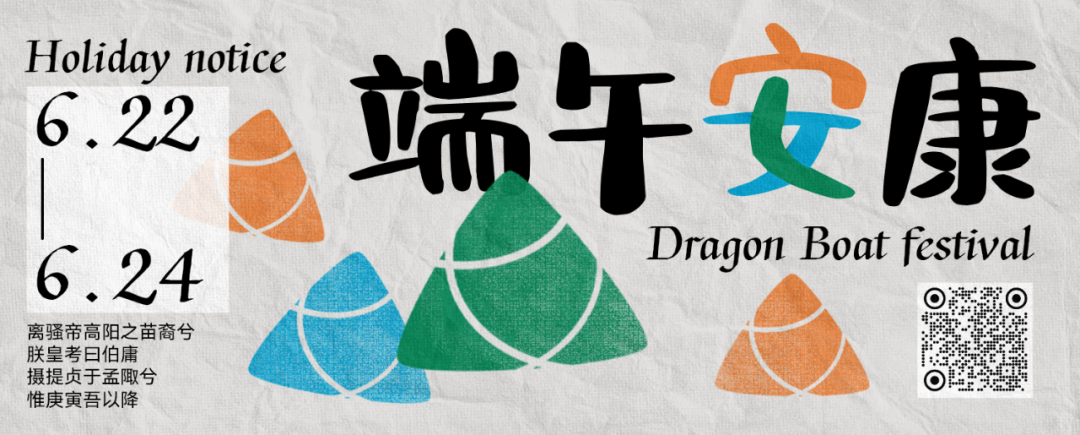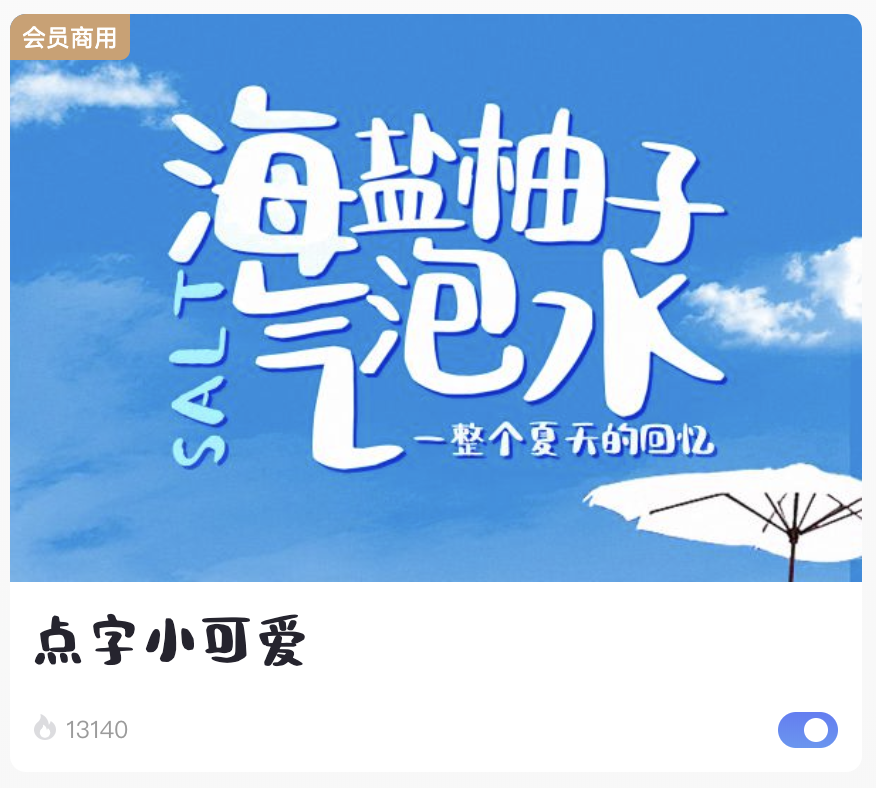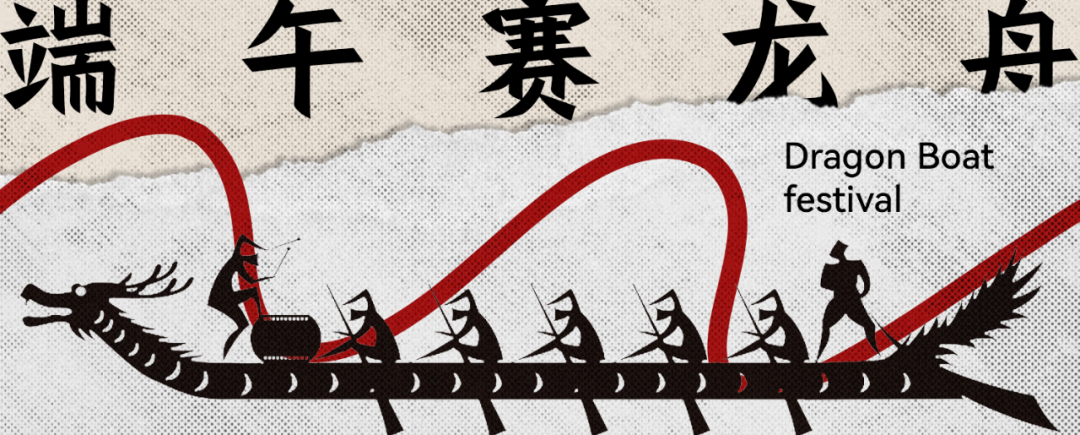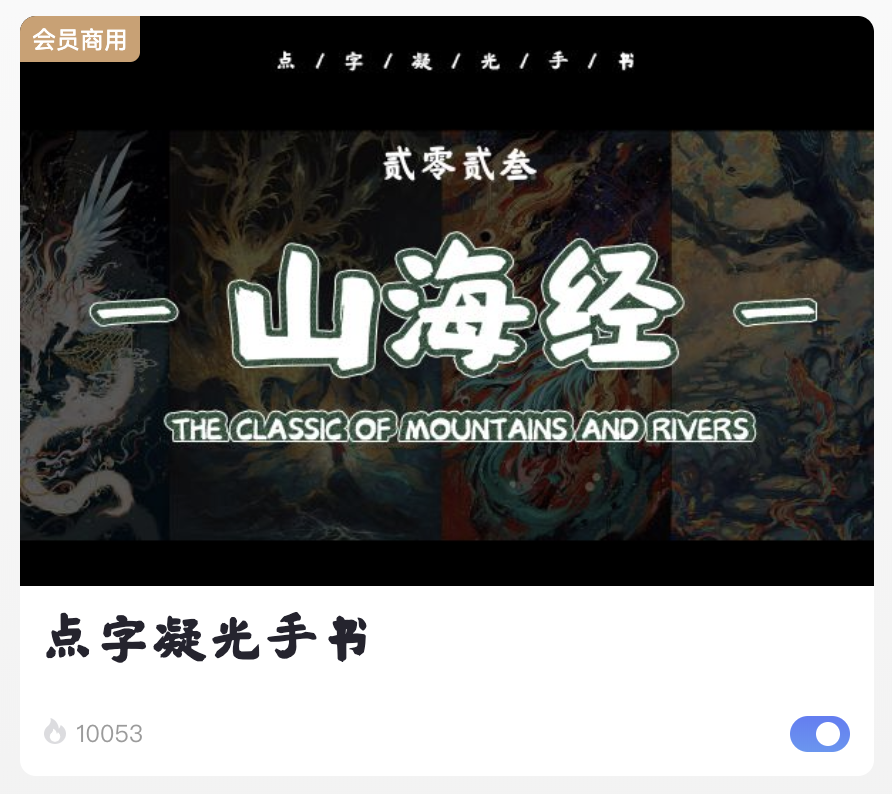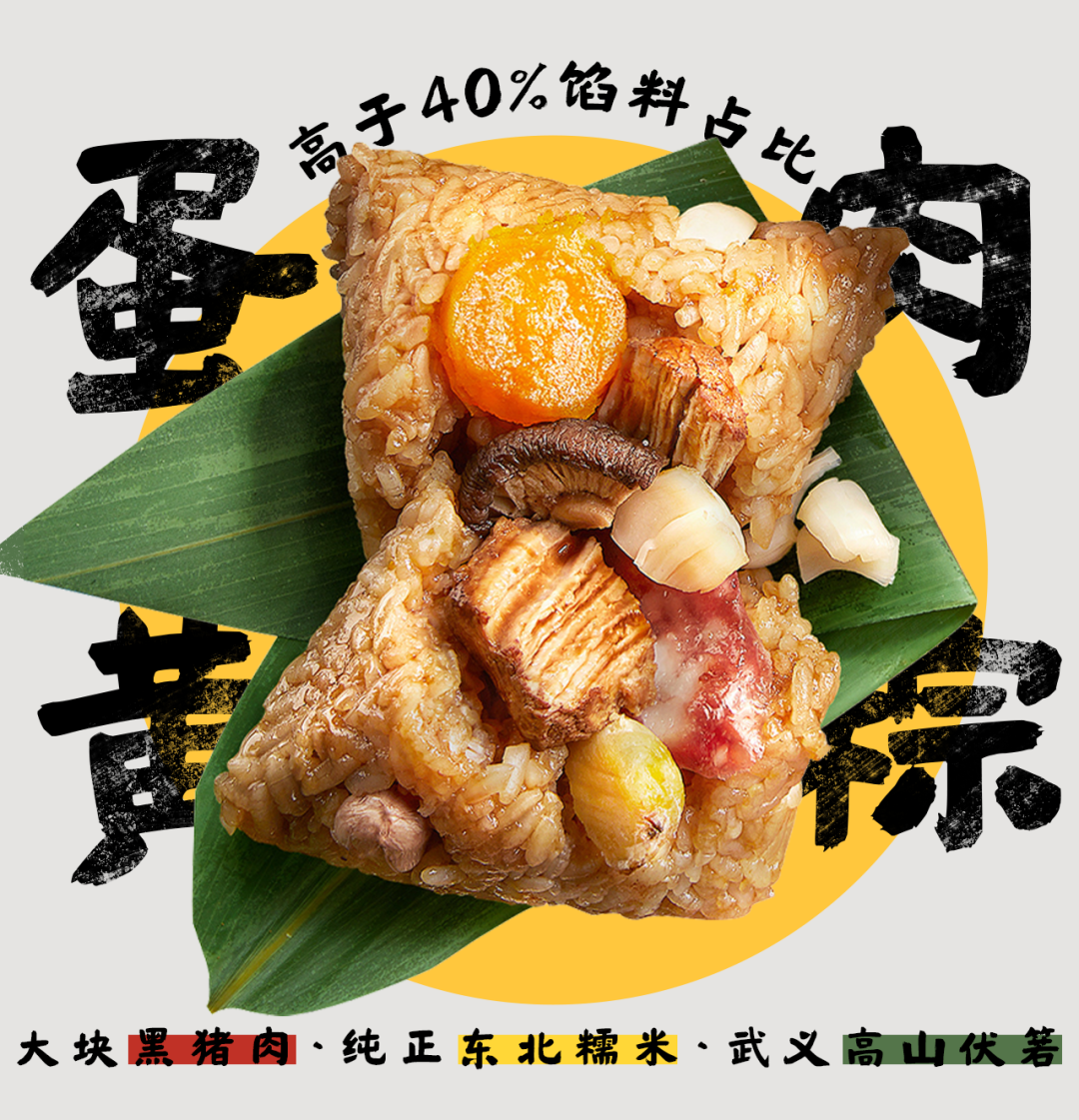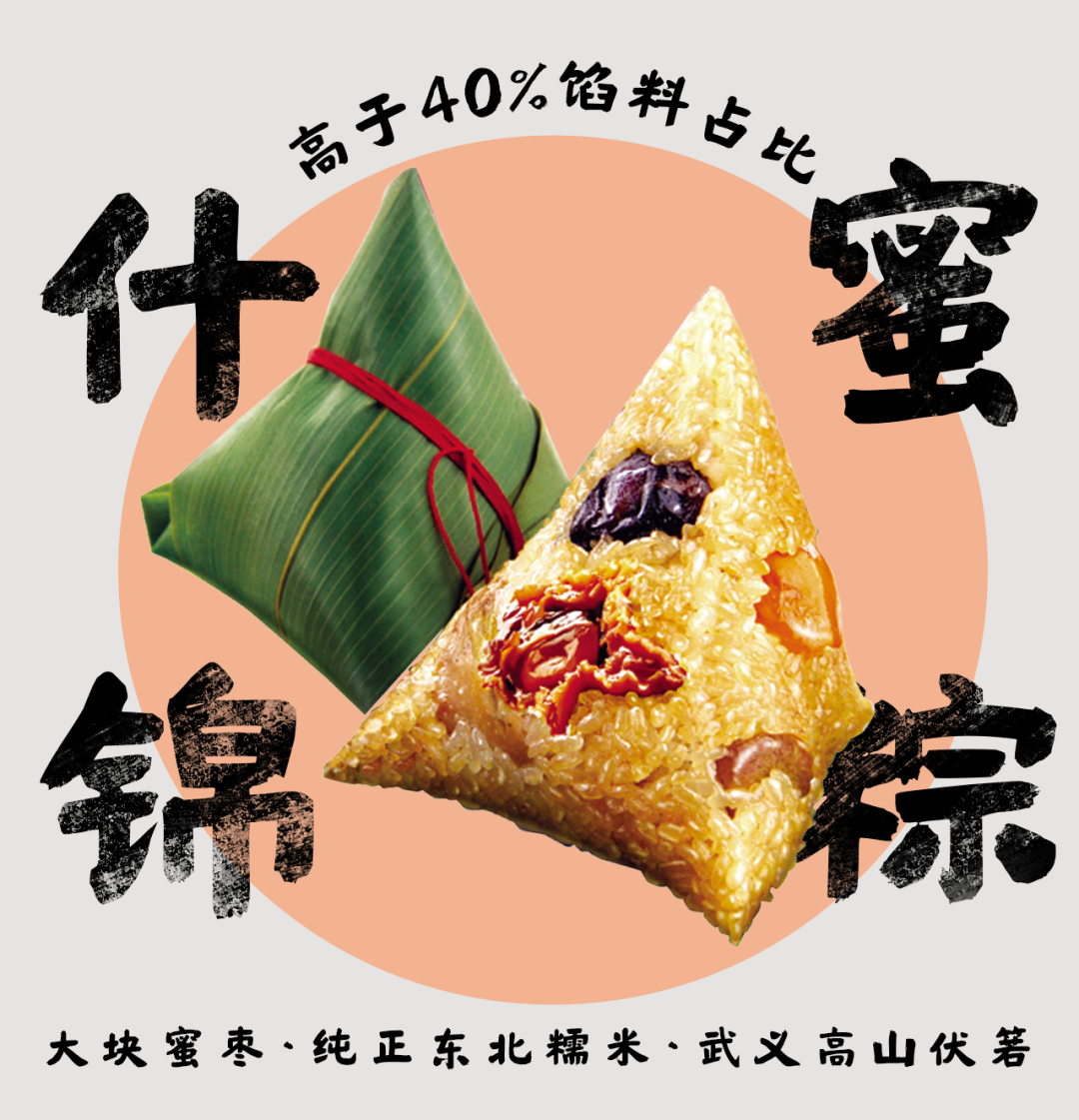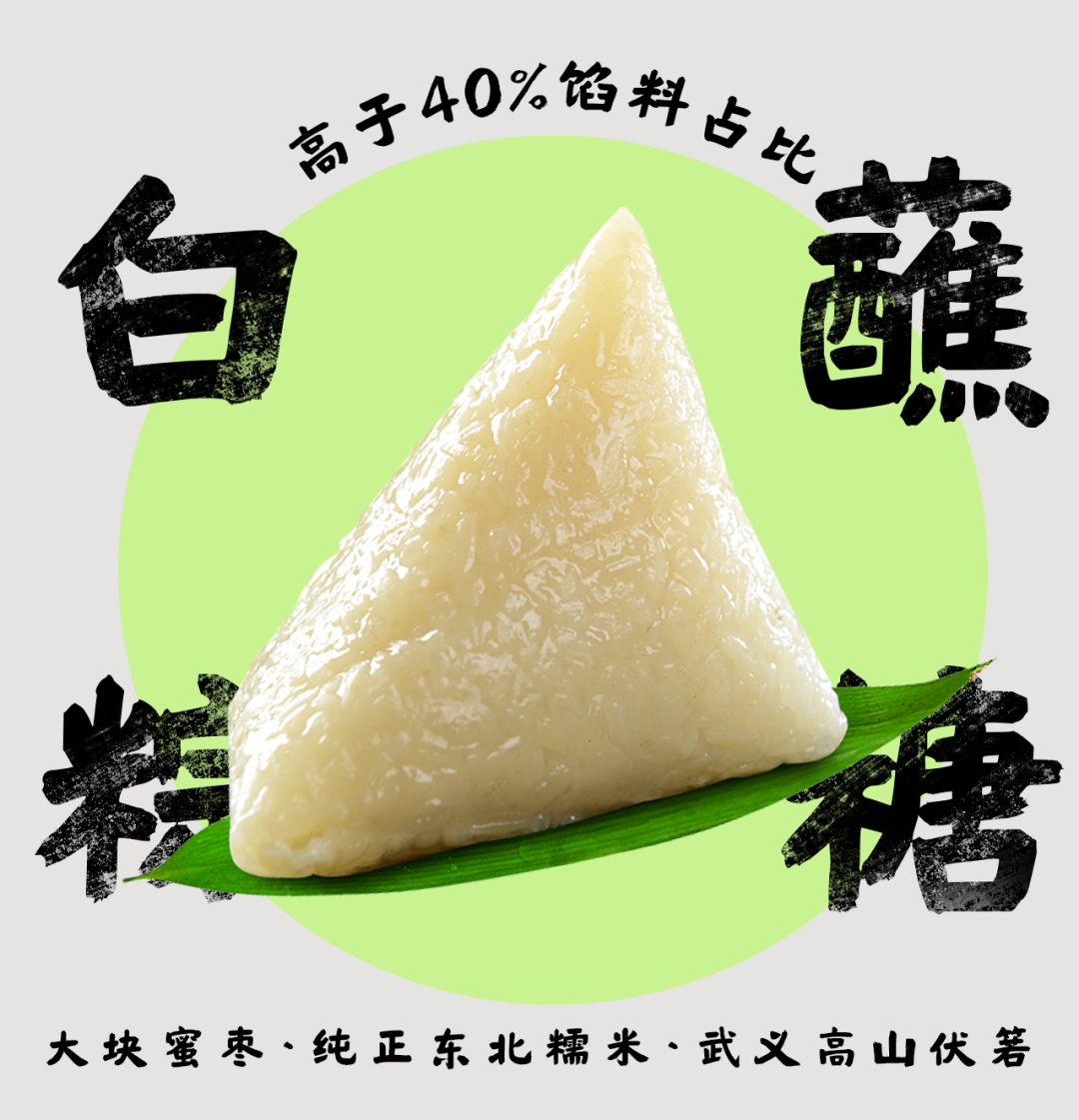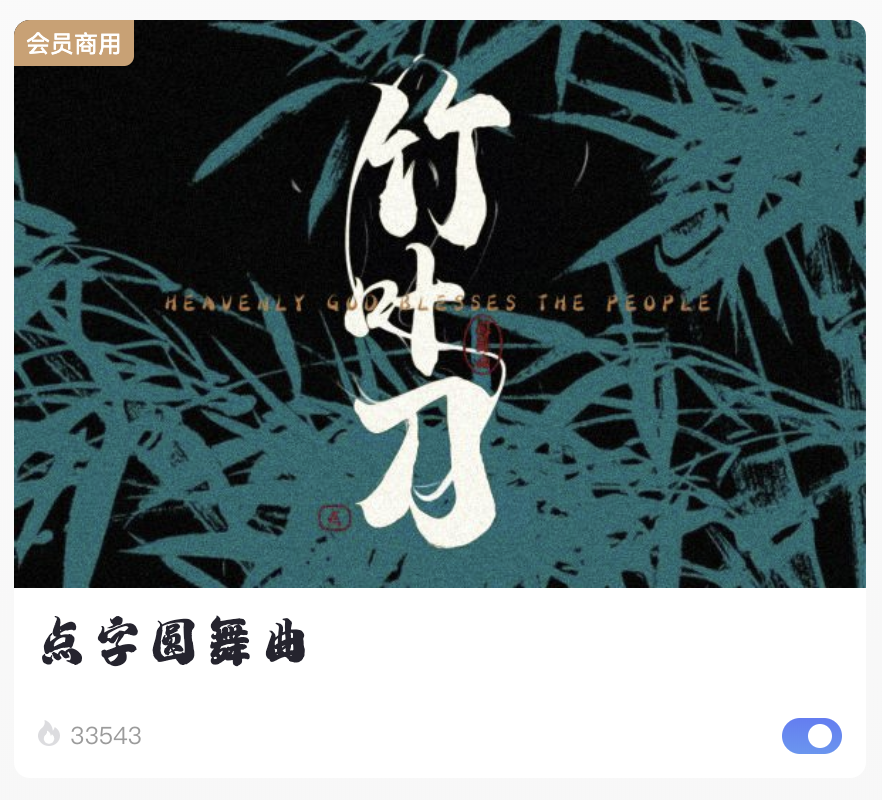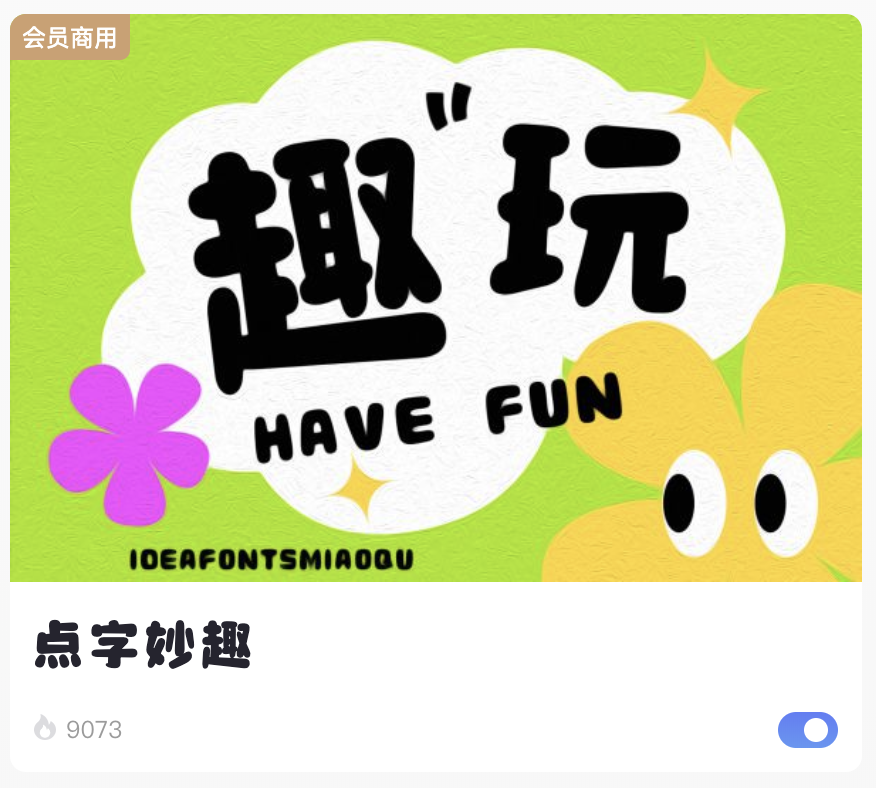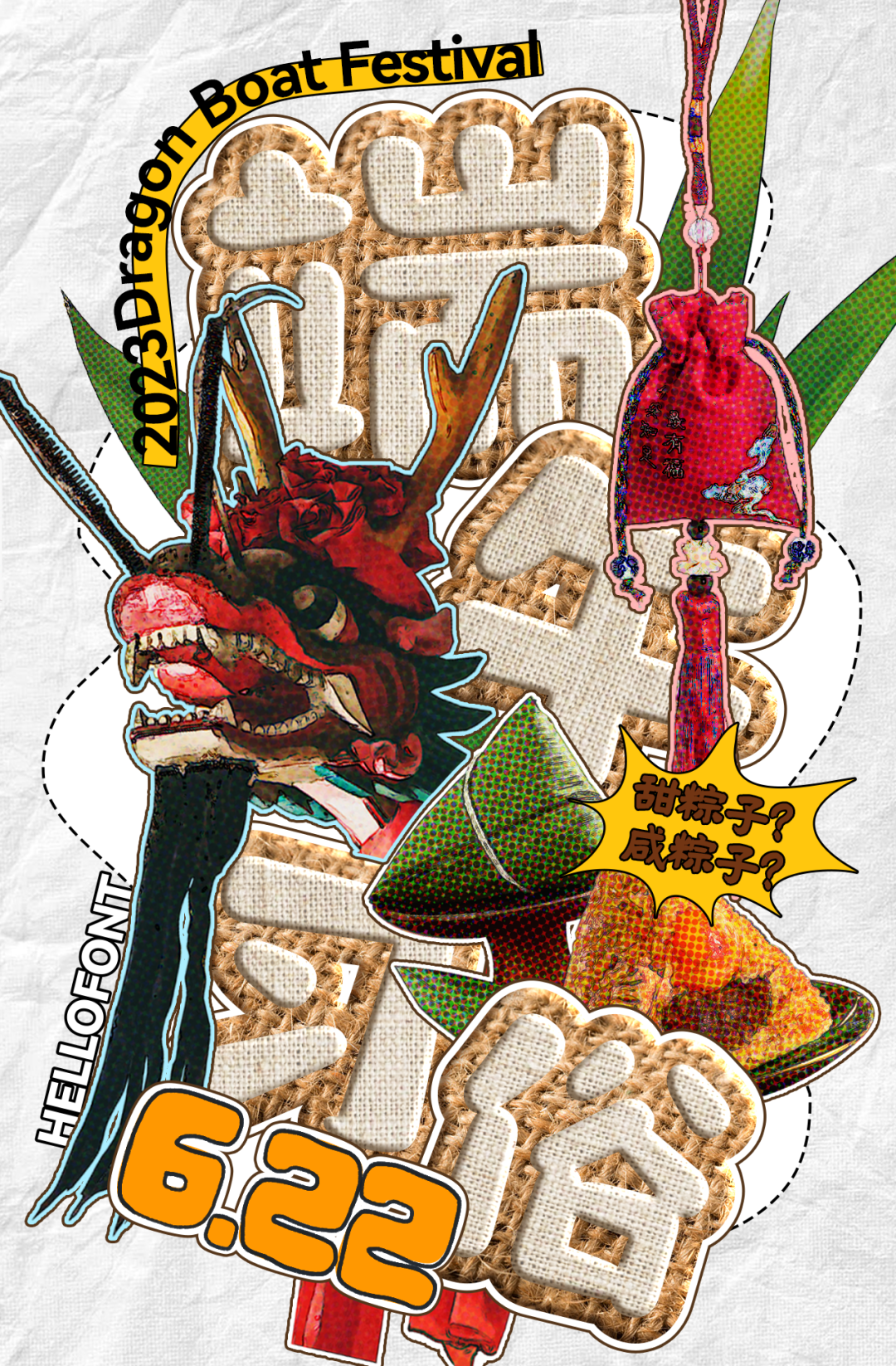
快速完成端午海报,这批新字太好用啦
唉……没办法,端午得过海报得做。节日海报嘛,先要整理一下这个节日的元素。那么端午的节日元素小伙伴们还记得吗?
先用点字小可爱祝大家端午安康~
△点字小可爱
吃货眼里的端午最重要的就是粽子咯~蜜枣粽,豆沙粽,蛋黄肉粽……你别说你还真别说,点字凝光手书真有那种“匠心50年,专业做粽子”的味道,又发现一个隐藏款美食海报适用字~😁
△点字凝光手书
再有就是赛龙舟和挂艾草了,点字佳楷端正的字形和微有棱角精致的轮廓也太适合节日海报了~
△点字佳楷
点字圆舞曲——别看名字这么西式,用起来可太有传统文化的那种古朴感了,获得“柚子觉得奈斯”认证
△点字圆舞曲
最后,用点字妙趣进行一个“端午元素大杂烩”的收尾,就算对字体进行一些夸张的设计,也不会影响文字的阅读呢~
△点字妙趣